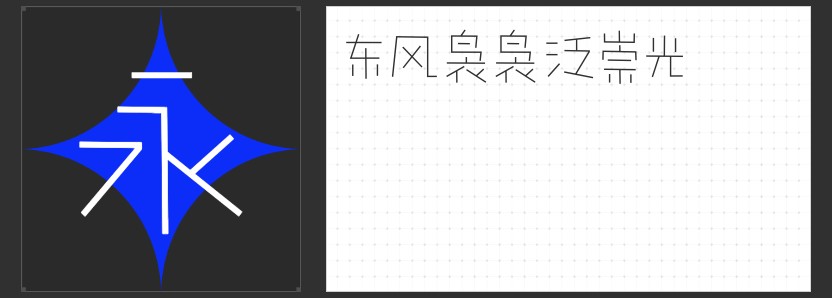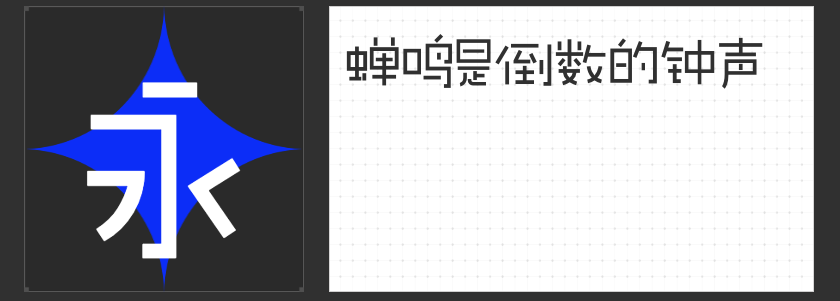
梦幻字体之旅:探索“字恋狂”系列的独特魅力
在文字的海洋里,每一款字体都承载着独特的情感与风格。今天,让我们一起踏上一段梦幻般的字体之旅,探索“字恋狂”系列中的四款瑰宝。
1.字恋狂漫野 拂风
这款字体如同其名,带着一股野性的浪漫与自由的风情。笔画间既有狂野不羁的肆意挥洒,又蕴含着细腻入微的精致雕琢。它仿佛是大自然中自由生长的藤蔓,随风摇曳,散发着独特的魅力。无论是用于标题还是正文,都能让人感受到一股扑面而来的野性与活力。
2.字恋狂澄空 拂风
与“漫野”的狂野不同,“澄空”更偏向于宁静与高远。它的笔画清晰流畅,宛如晴空万里下的云朵,轻盈而优雅。这款字体能够营造出一种清新脱俗的氛围,让人仿佛置身于蓝天白云之下,心情舒畅。它非常适合用于需要展现清新、自然风格的文本设计。
3.字恋狂嗨玩简
这款字体则充满了年轻与活力。它的笔画简洁明快,线条流畅,给人一种轻松愉悦的感觉。无论是用于社交媒体、广告海报还是游戏界面,都能让人眼前一亮,瞬间吸引注意力。它仿佛是一位年轻的艺术家,用最简单的笔触描绘出最生动的画面。
4.字恋狂白日梦简
最后,我们来看看这款充满梦幻色彩的“白日梦简”。它的笔画柔和而富有想象力,仿佛是一位正在编织白日梦的画家,用文字描绘出一个又一个美丽的梦境。这款字体非常适合用于需要激发读者想象力的文本设计,如童话故事、科幻小说等。
总之,“字恋狂”系列中的这四款字体各有千秋,无论是追求狂野与自由、宁静与高远、年轻与活力还是梦幻与想象,都能在这四款字体中找到满足自己需求的那一款。让我们一同在文字的海洋中畅游,感受不同字体带来的独特魅力吧!